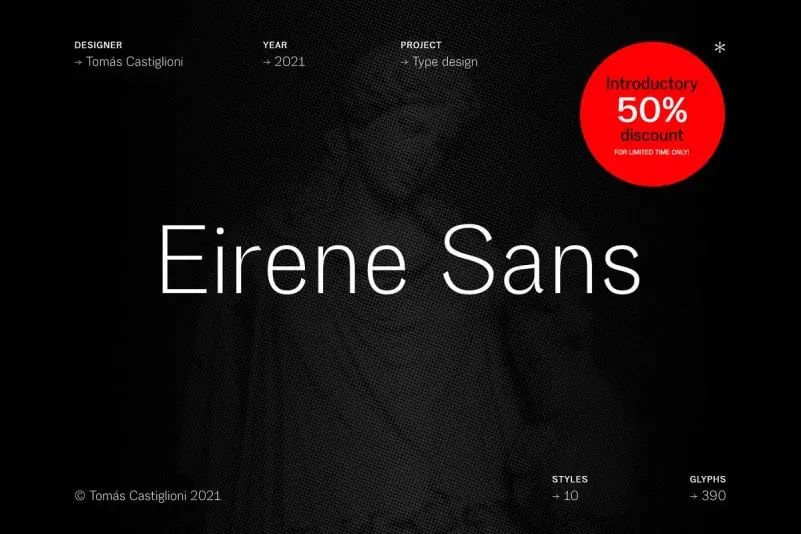
A Eirene Sans é uma família de fontes sans-serif minimalista com todas as características essenciais de um tipo de linhas retas perfeitamente finos, sendo ideal para design gráfico, apresentação de texto, web design e imprensa. Inspirada nos humanistas, a Eirene Sans incorpora alguns elementos grotescos, proporcionando um visual simples e moderno. Este é um projeto funcional que destaca os caracteres maiúsculos com uma personalidade sofisticada. A família tem cinco pesos diferentes disponíveis, incluindo itálicas para complementar cada uma dessas opções. Embora ligeiramente condensada em relação à ampliação normal, a Eirene Sans apresenta um contraste único entre os traços finos e grossos que conferem ao tipo sua personalidade humanista. Este é o ponto de partida perfeito para aqueles que buscam uma fonte clara e moderna, capaz de se adaptar com fluidez em qualquer ambiente visual digital ou impresso.